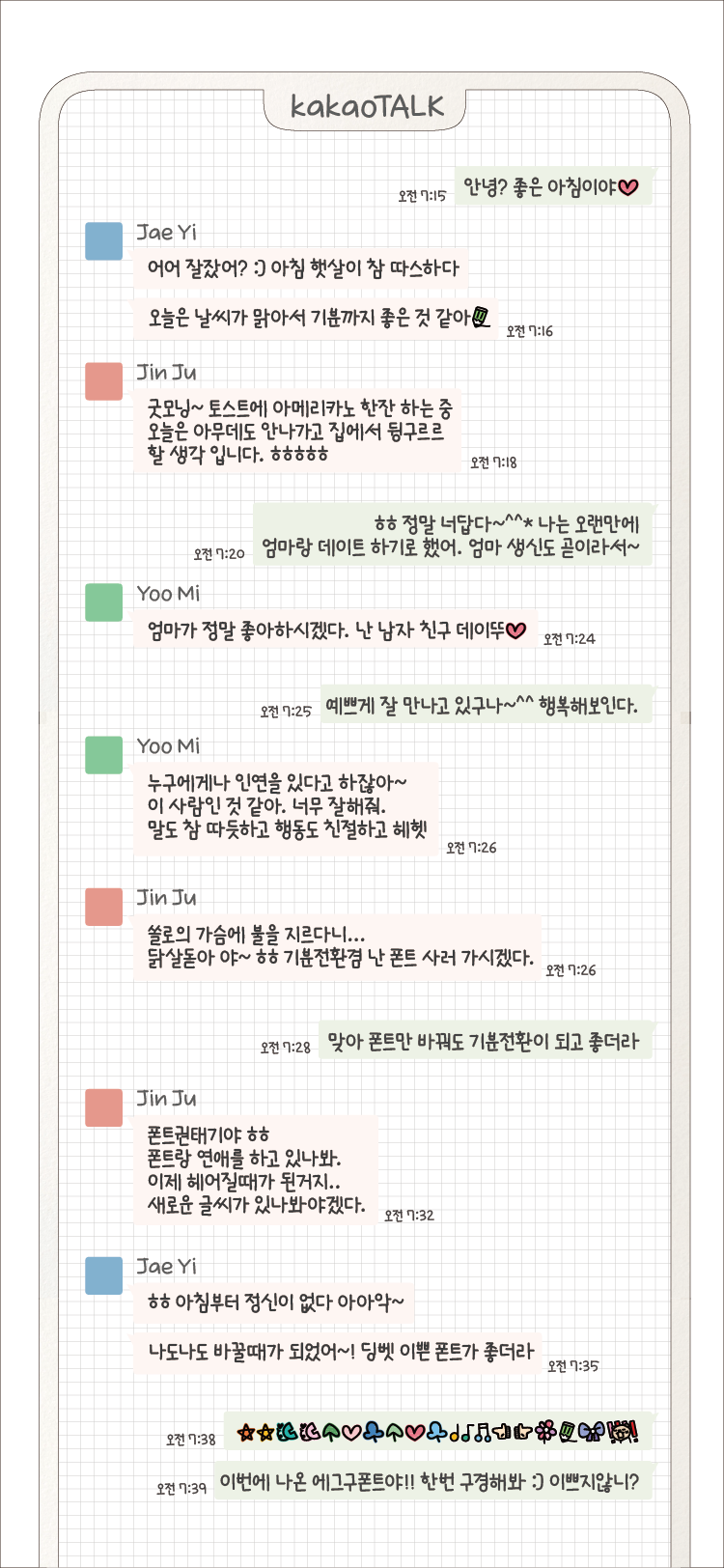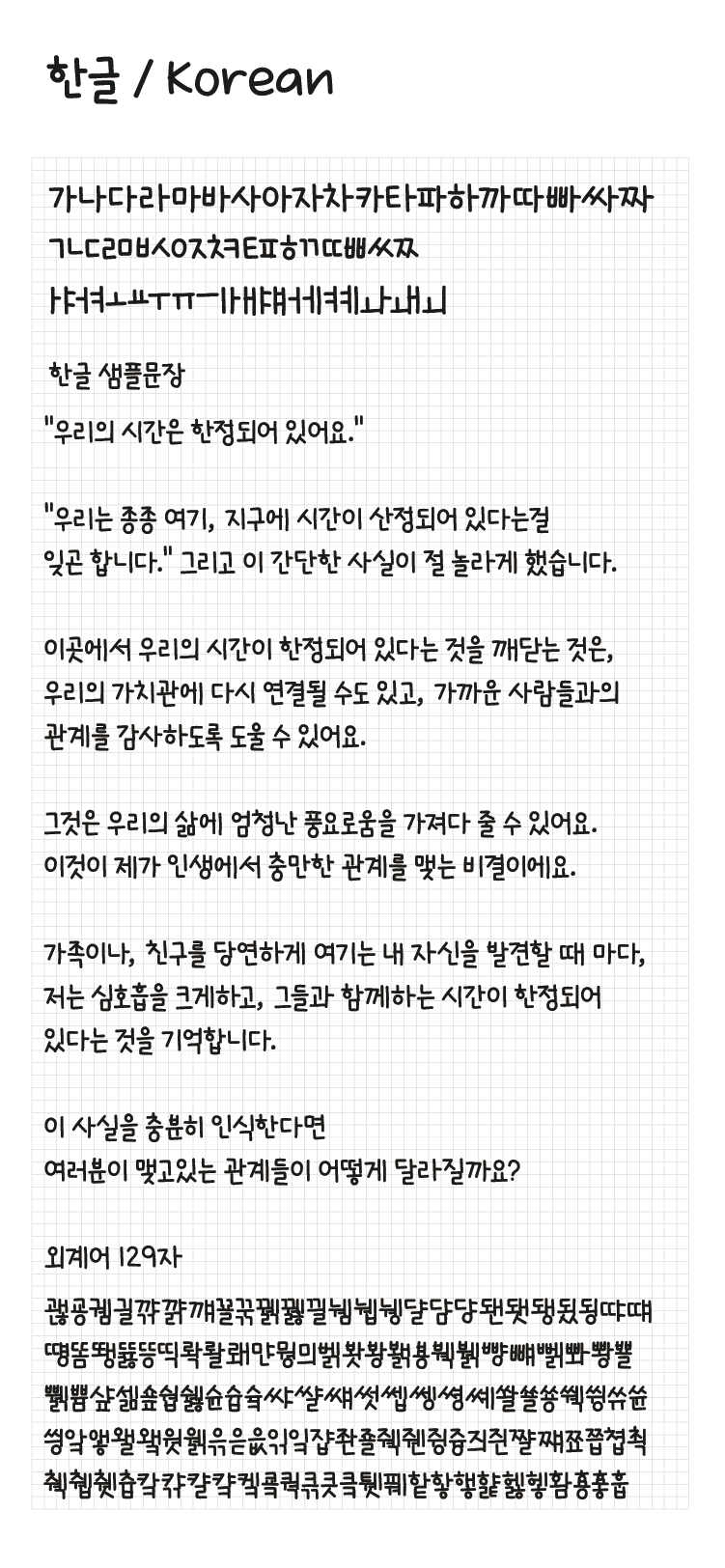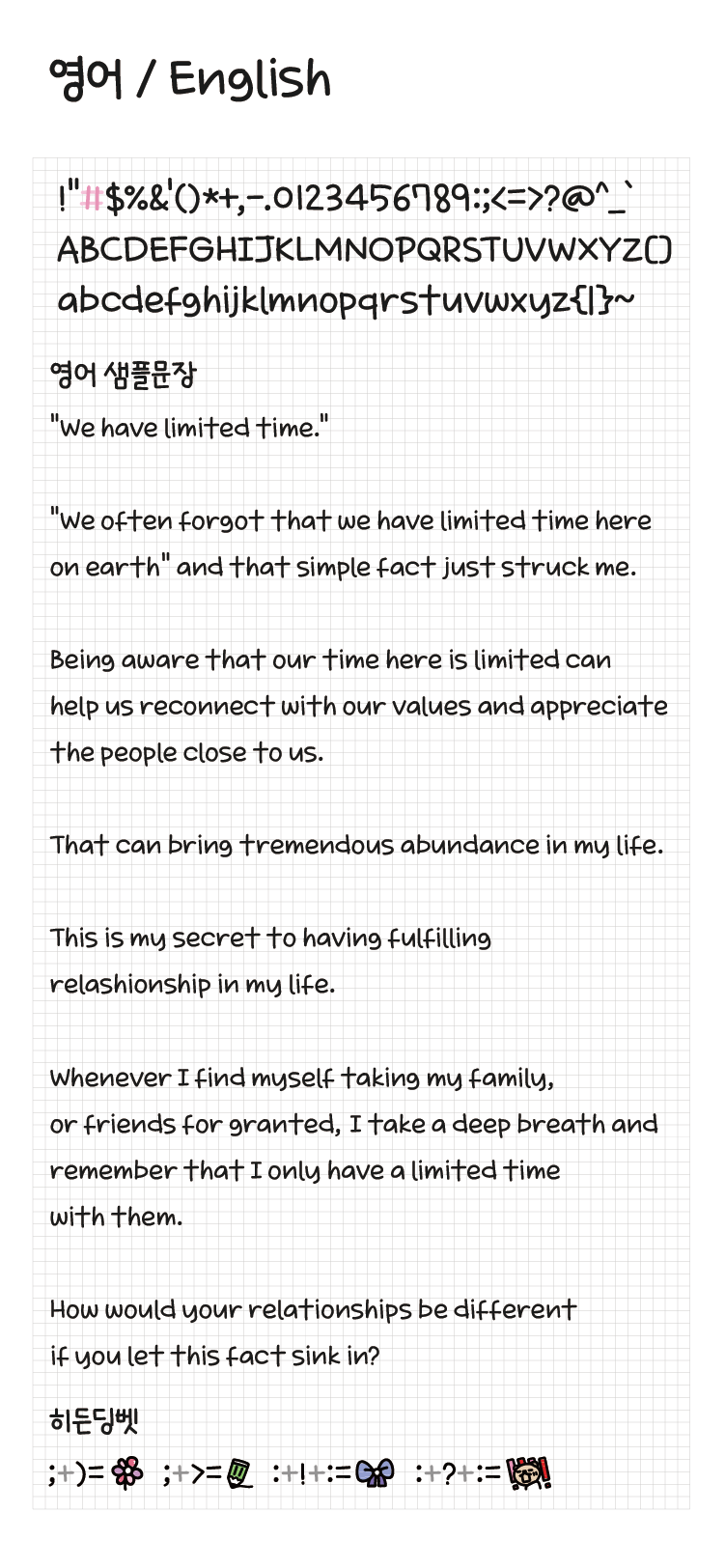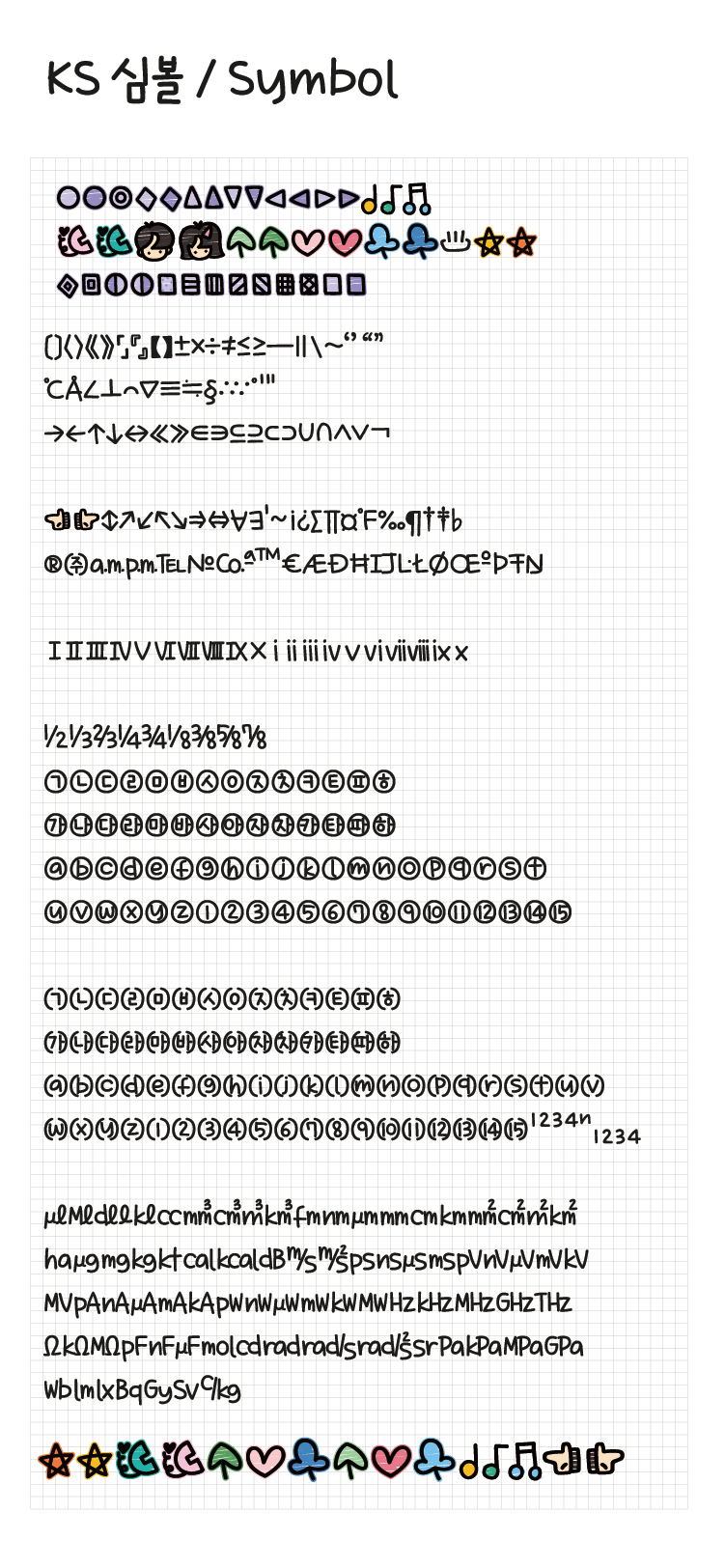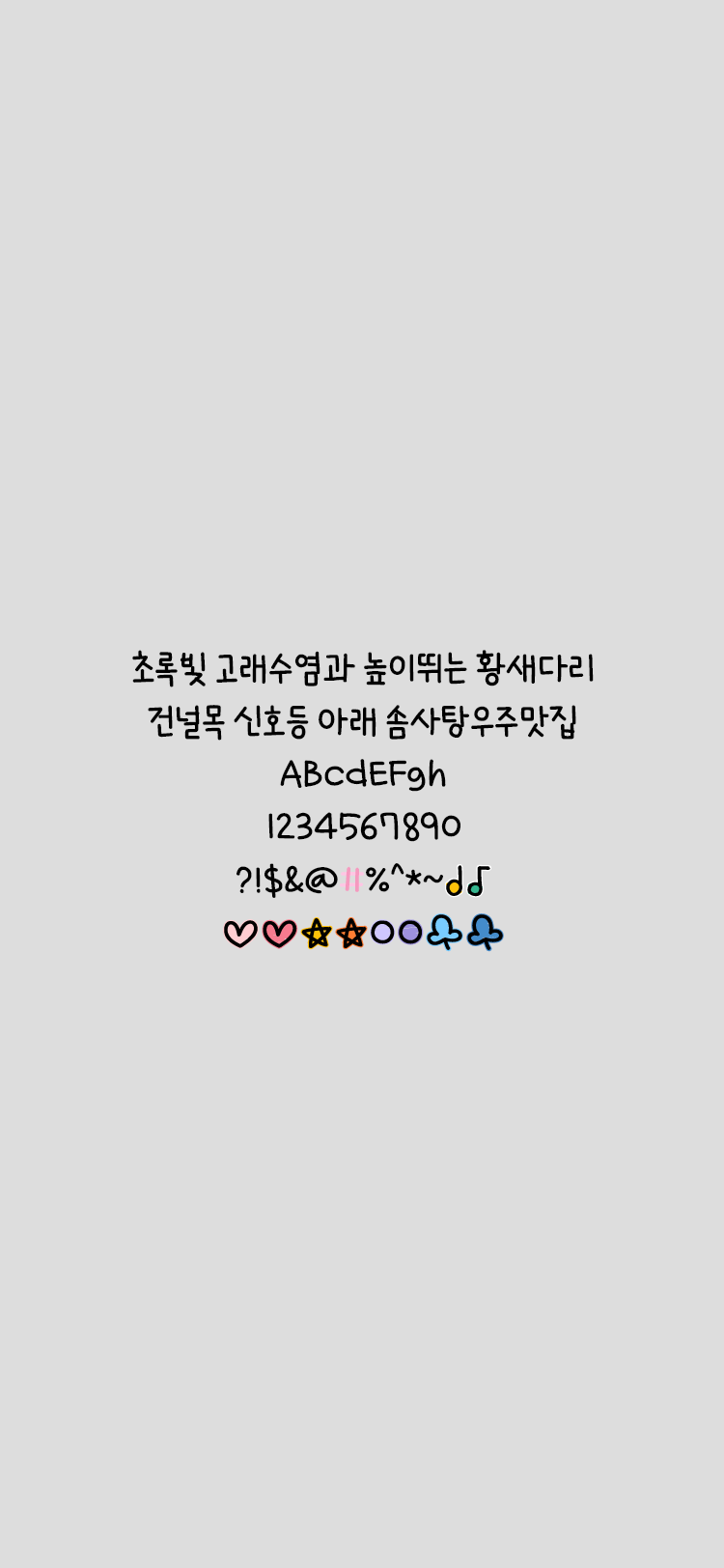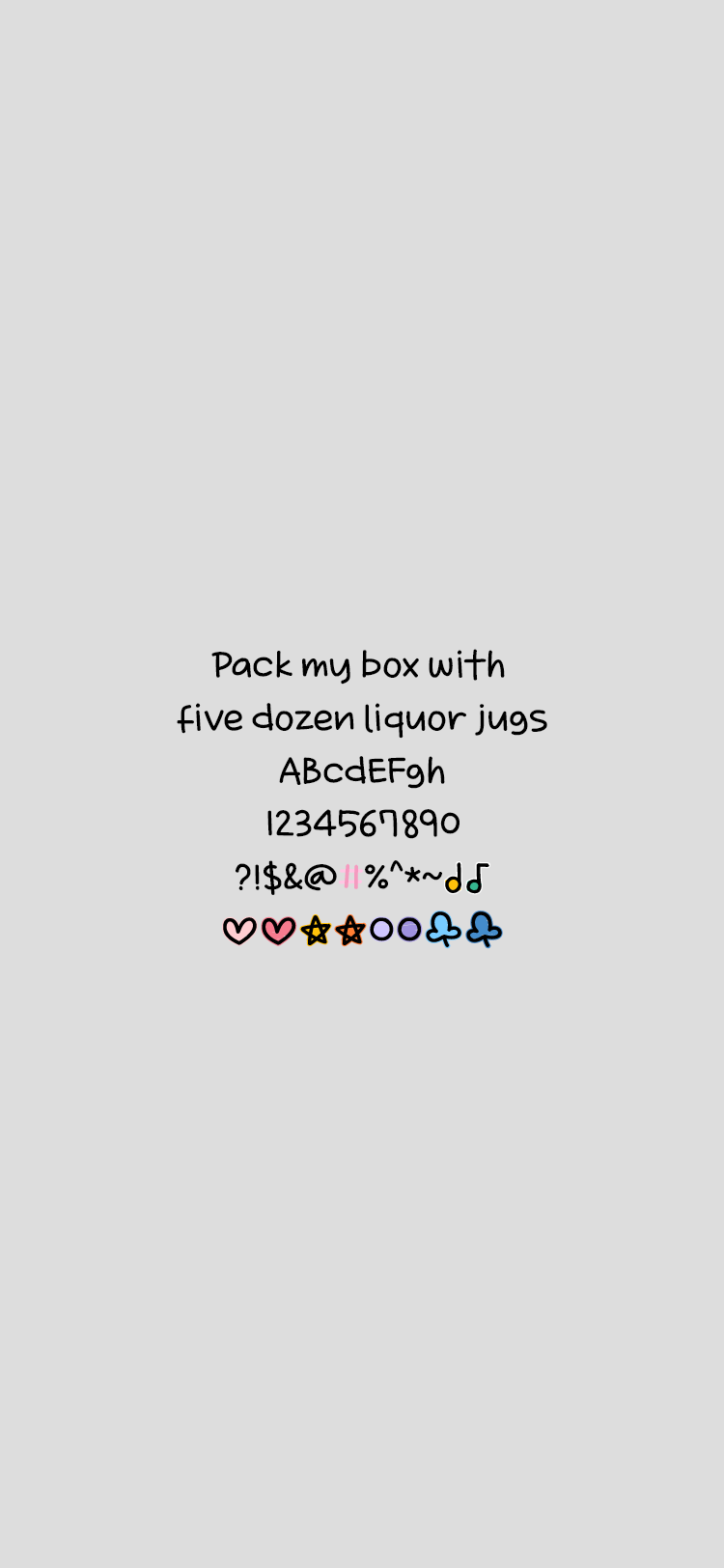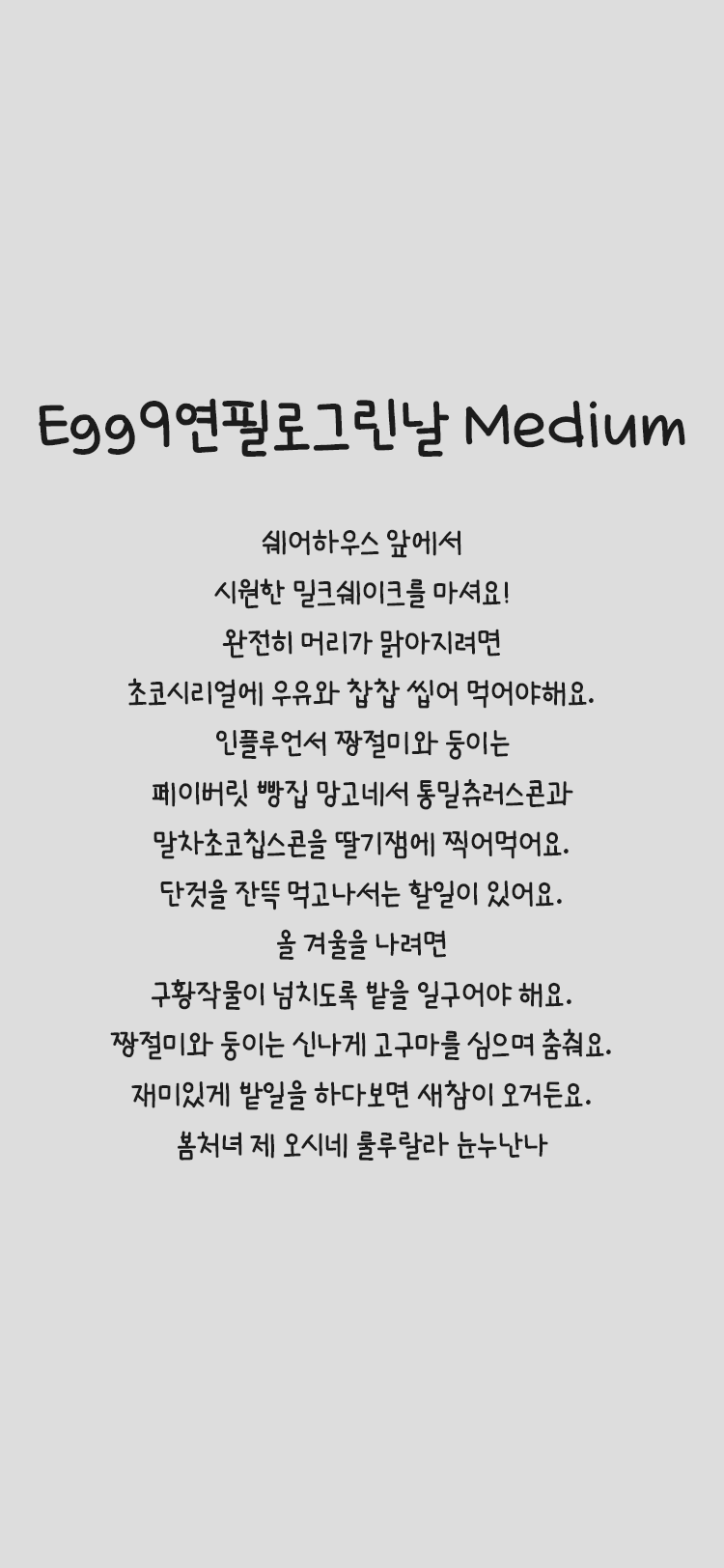
Egg9 연필로그린날 Medium
안녕하세요. 기존에 나간 Egg9연필로그린날(Egg9_DrawingDay)이 이번에 Egg9연필로그린날 Medium 버젼 올립니다.
기존 Egg9연필로그린날> Egg9연필로그린날 Regular로 변경했습니다.
아기자기한 손글씨 스타일입니다. 히든딩벳의 경우 ;> ;) :!: :?: 입력하시면 나옵니다.